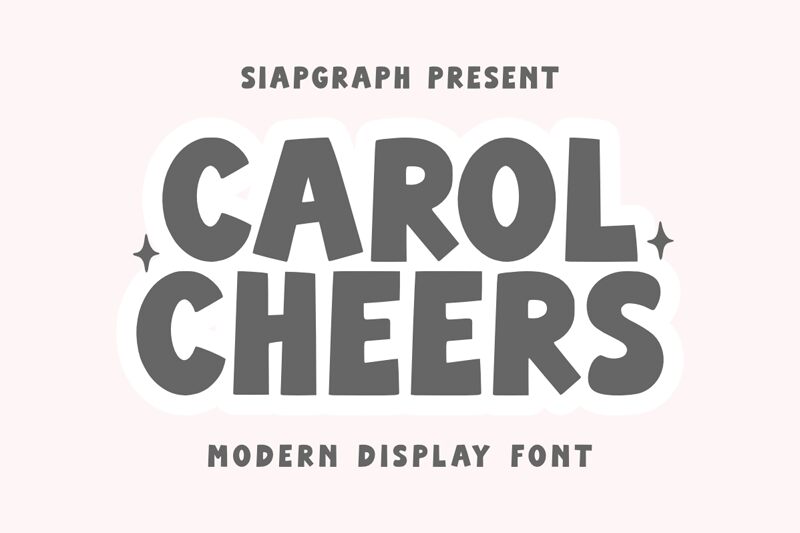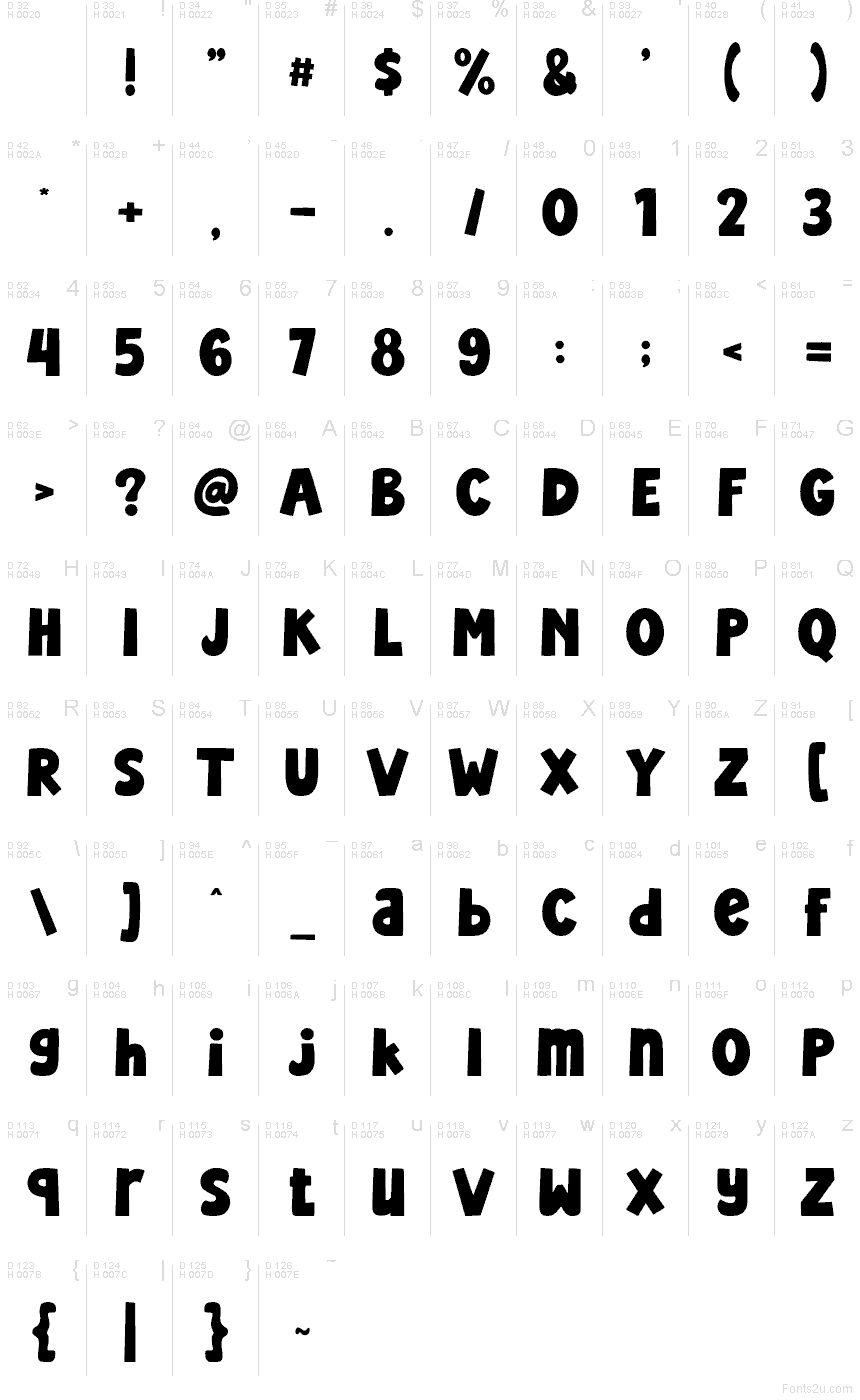
Carol Cheers Regular
Carol Cheers od SiapGraph je bezplatné kreslené písmo, definované veľkými zaoblenými tvarmi a mierne asymetrickými rezmi, vďaka ktorým pôsobia písmená ručne kresleným dojmom namiesto príliš uhladeného vzhľadu. Táto nepravidelná silueta dodáva každému znaku živú, takmer až stlačenú podobu, takže písmo funguje oveľa lepšie ako hravý nadpis než ako štandardné dekoratívne písmo.
Skvele sa hodí na pozvánky na narodeninové oslavy, detské plagáty, školské projekty, obaly na sladkosti či veselú grafiku pre sociálne siete, kde potrebujete, aby krátke slová pôsobili mäkko a výrazne. Vďaka svojim širokým a jednoduchým tvarom, ktoré si zachovávajú svoju energiu, sa Carol Cheers výborne hodí aj pre dizajn nálepiek alebo branding hračiek bez toho, aby pôsobilo príliš upäto alebo formálne.